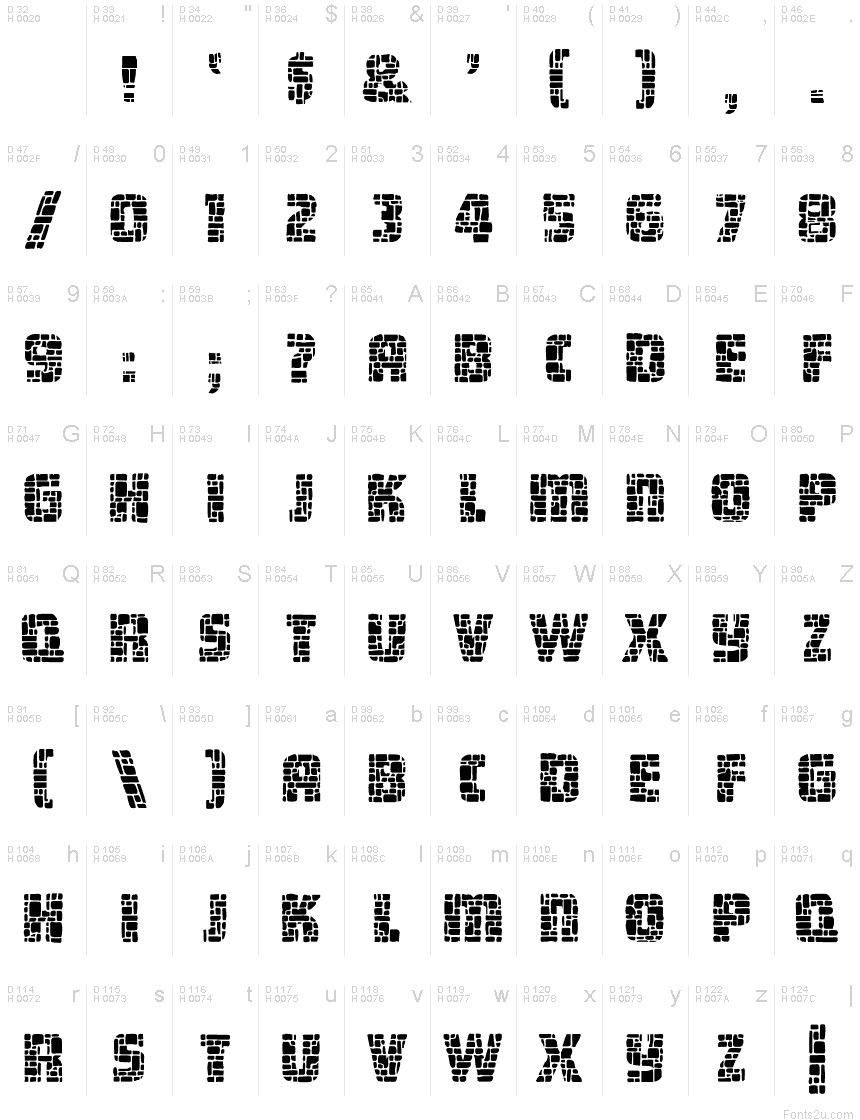
Dungeon Blocks Filled di Dave Fabik è un font display decorativo gratuito che trasforma ogni parola in un muro di pietra in rovina. Le sue lettere tozze e a griglia sono piene di spazi irregolari che ricordano crepe, tunnel e passaggi segreti scavati in blocchi solidi. Il risultato è una texture audace e "rumorosa" che mantiene una silhouette chiara; i tuoi titoli colpiranno nel segno, sembrando costruiti con mattoni da dungeon e corridoi nascosti.
Utilizzando Dungeon Blocks Filled, puoi dare istantaneamente ai loghi di giochi, ai titoli per giochi di ruolo da tavolo, ai poster di escape room, ai volantini per eventi fantasy, alle miniature di YouTube e al merchandise a tema un'atmosfera cruda e underground. Questo font gratuito dà il meglio di sé nelle grandi dimensioni, dove il motivo a blocchi può davvero respirare. Abbinalo a un semplice font sans serif geometrico per il testo principale e lascia molto spazio attorno per far sì che le forme labirintiche rimangano leggibili e d'impatto.